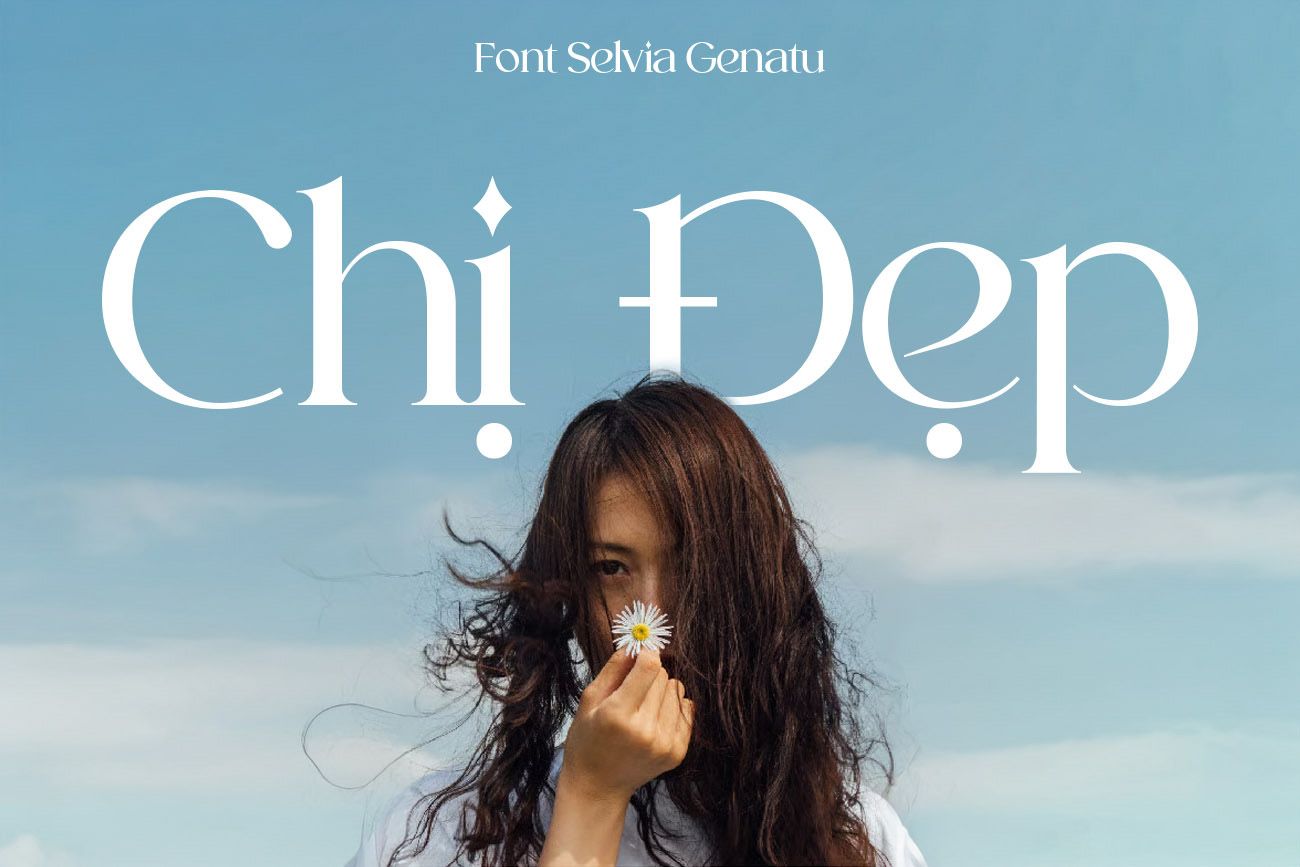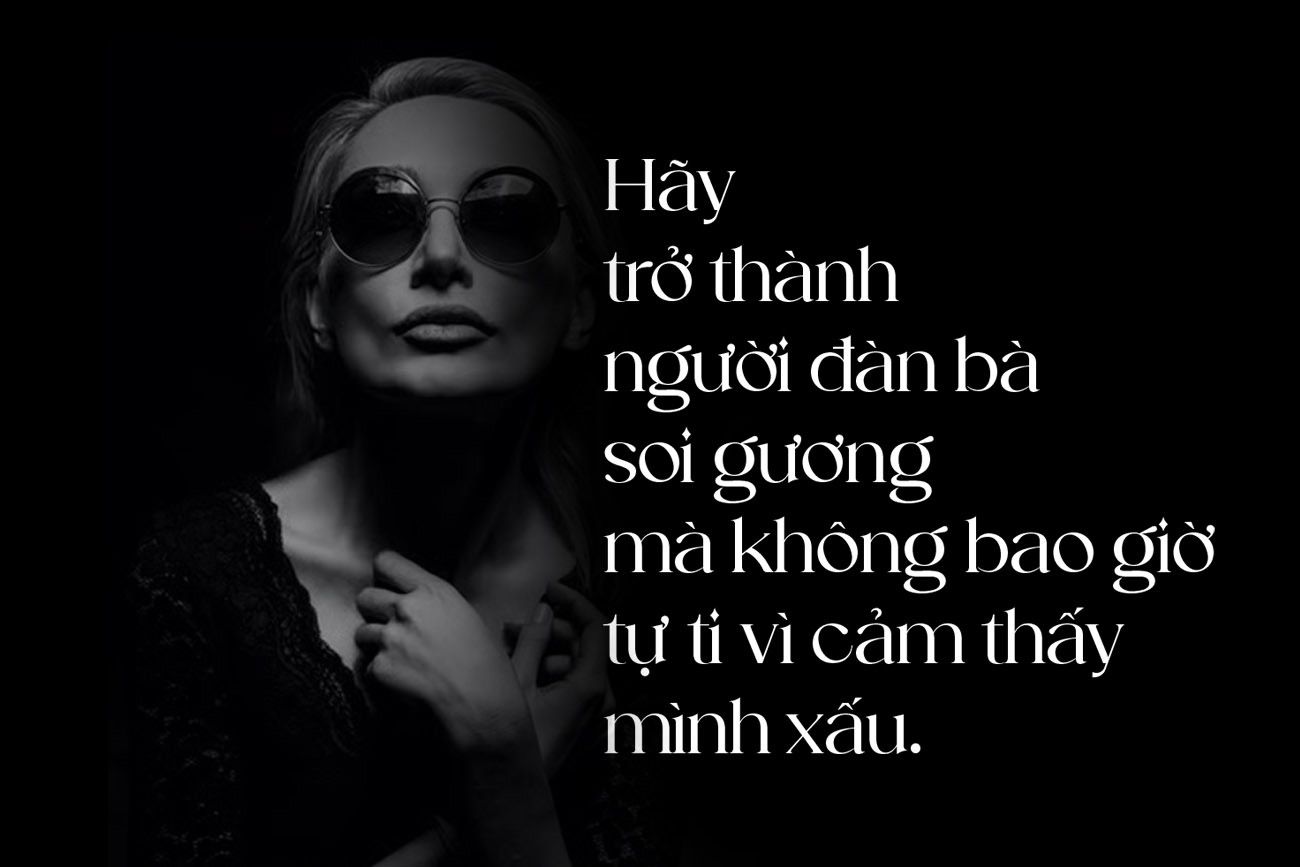
Nếu bạn đang tìm kiếm một biểu tượng của sự thanh lịch và đẳng cấp, TH Selvia Genatu Việt hóa chính là sự lựa chọn không thể bỏ qua. Thuộc dòng Serif (có chân) hiện đại, font chữ này gây ấn tượng mạnh mẽ bởi sự tương phản tinh tế giữa những nét đưa mảnh khảnh và thân chữ dày dặn, tạo nên một cấu trúc cân đối, đầy tính nghệ thuật.
TH Selvia Genatu mang trong mình hơi thở của những kinh đô thời trang và tạp chí cao cấp. Bản Việt hóa đã được tinh chỉnh tỉ mỉ, giúp các dấu tiếng Việt giữ nguyên vẻ thanh thoát mà không làm mất đi linh hồn sang trọng vốn có của bộ chữ. Đây là "vũ khí" hoàn hảo cho các nhà thiết kế khi thực hiện:
Bộ nhận diện thương hiệu: Spa, mỹ phẩm, trang sức cao cấp.
Thiết kế thiệp mời: Mang lại vẻ ngoài chỉn chu, quý phái.
Layout dàn trang: Tạo điểm nhấn tiêu đề đầy cuốn hút.
Với TH Selvia Genatu, mỗi con chữ đều toát lên thần thái tự tin, biến mọi bản thiết kế trở thành một tác phẩm nghệ thuật thượng lưu.